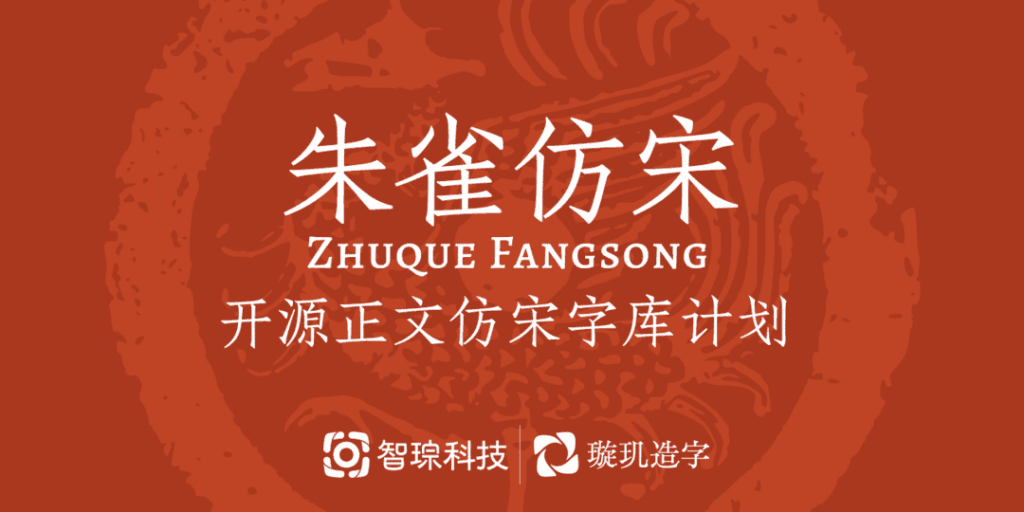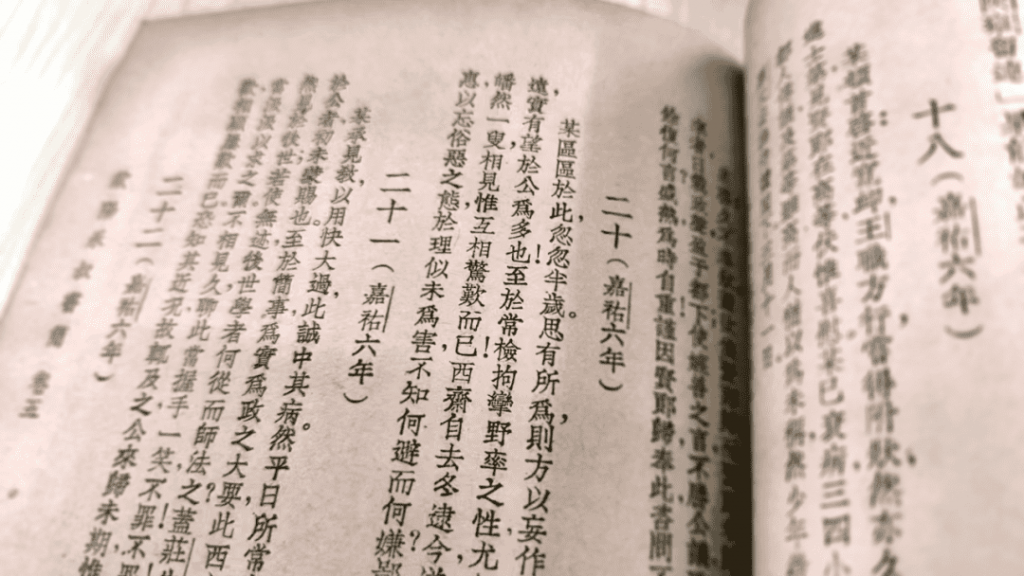
「朱雀仿宋」是璇玑造字的开源仿宋字体计划,志在最终提供高质量的、支持多语言的正文仿宋解决方案。
仿宋作为「宋黑仿楷」中文四大基础字体之一,长期缺乏开源许可证下的选择。我们希望「朱雀仿宋」可以弥补这一空缺,为开源软件与 TeX 社区贡献一份力。
上世纪初,仿宋活字一度品类繁盛,开发、应用风行一时。然而时过境迁,市面上的仿宋最终收敛于「华丰真宋」一系,这也是今天大多数人所熟悉的仿宋样貌。「朱雀仿宋」则以民国仿宋活字「南宋」为蓝本,在满足现代排印需求的前提下,尝试为正文仿宋字库带来一缕新鲜空气。
当前我们发布的「朱雀仿宋」仍为「预览测试版」,尚处于项目早期阶段;无论是设计风格还是字形、排版质量,都不代表正式版情况。因此,
璇玑正在尝试一种全新中文字库设计模式。得益于我们开发的最新技术,璇玑的设计师可以直接将人工智能作为设计工具去使用,我们也因此能以迭代的方式开发「朱雀」。
智琮的智能造字技术可以让设计师将 AI 作为设计工具去使用,可快速从拼字甚至是手写字优化成高质量的风格字形。
开发一套开源仿宋字库的想法最早始于 2021 年初,是继「未来荧黑」项目之后,我们认为更有意义、也更具难度的挑战。随着设计研究的深入与技术进步,特别是去年以来 AIGC 技术的爆发,实现这一想法在今日遂成可能。
「朱雀仿宋」改刻自民国活字「南宋」,试图为这套沉睡数十年的字体赋予新生。「南宋」是 1932 年「百宋书局」推出的仿宋体活字,韩佑之设计原稿,邹根培雕刻字模。一经面世,即广泛用于书籍、期刊排印。「南宋」与大多数正文字体的设定不同的是,它中宫收紧,重心略靠右下,撇捺舒展,笔画的粗细变化强烈,含蓄秀美而充满力量感,在排印标题和正文时展现出浓厚的「书卷气」。
在「南宋」活字的基础上,「朱雀仿宋」稍稍削弱了笔画的对比度,适当地规整了字形结构与版面效果,同时最大程度地保留了「南宋」的独特气质与活字趣味。
「朱雀」是中国传统文化中「四象」之一,南方七宿之神。以「朱雀」为名,暗合了「南宋」渊源与「璇玑造字」的品牌名。